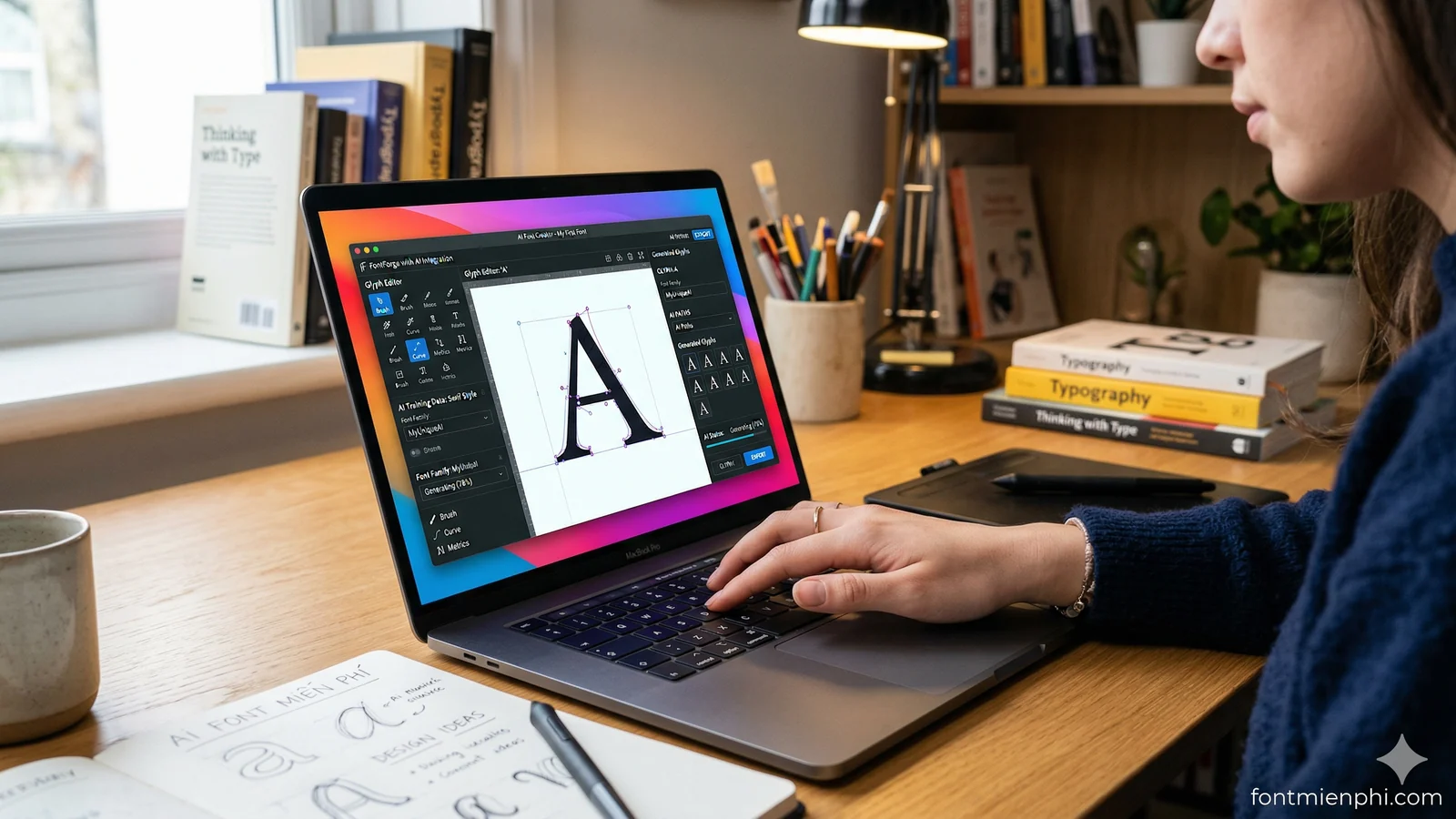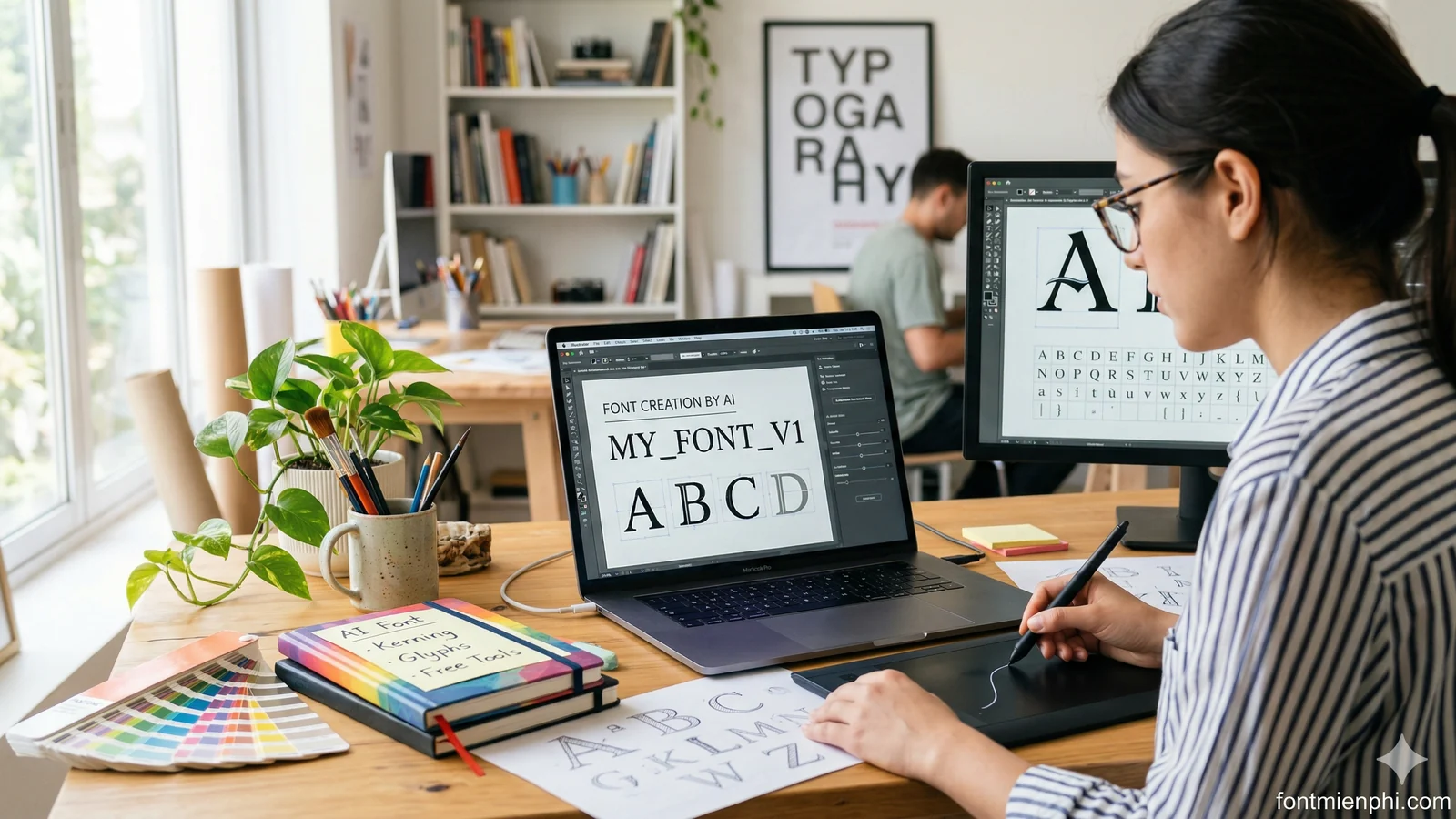
Bài viết này cung cấp hướng dẫn chi tiết về quy trình thiết kế bộ phông chữ cá nhân hóa bằng công nghệ trí tuệ nhân tạo mà không tốn chi phí. Bạn sẽ được tìm hiểu từ bước lên ý tưởng, sử dụng các công cụ AI tạo hình chữ cái cho đến việc số hóa chúng thành tệp định dạng chuẩn, giúp người mới bắt đầu dễ dàng làm chủ nghệ thuật chữ viết kỹ thuật số.
Cách Tạo Font Chữ Riêng Bằng AI Miễn Phí Dành Cho Người Mới
Thế giới thiết kế đồ họa đang trải qua một cuộc cách mạng mạnh mẽ nhờ sự can thiệp của trí tuệ nhân tạo. Trước đây, việc tạo ra một bộ phông chữ hoàn chỉnh đòi hỏi hàng tháng trời làm việc tỉ mỉ với các đường vector và kiến thức chuyên sâu về khoảng cách chữ. Tuy nhiên, hiện nay, ngay cả những người không có nền tảng về thiết kế cũng có thể tự tạo cho mình một bộ font chữ độc bản chỉ trong vài giờ đồng hồ nhờ sự hỗ trợ của các công cụ AI miễn phí.
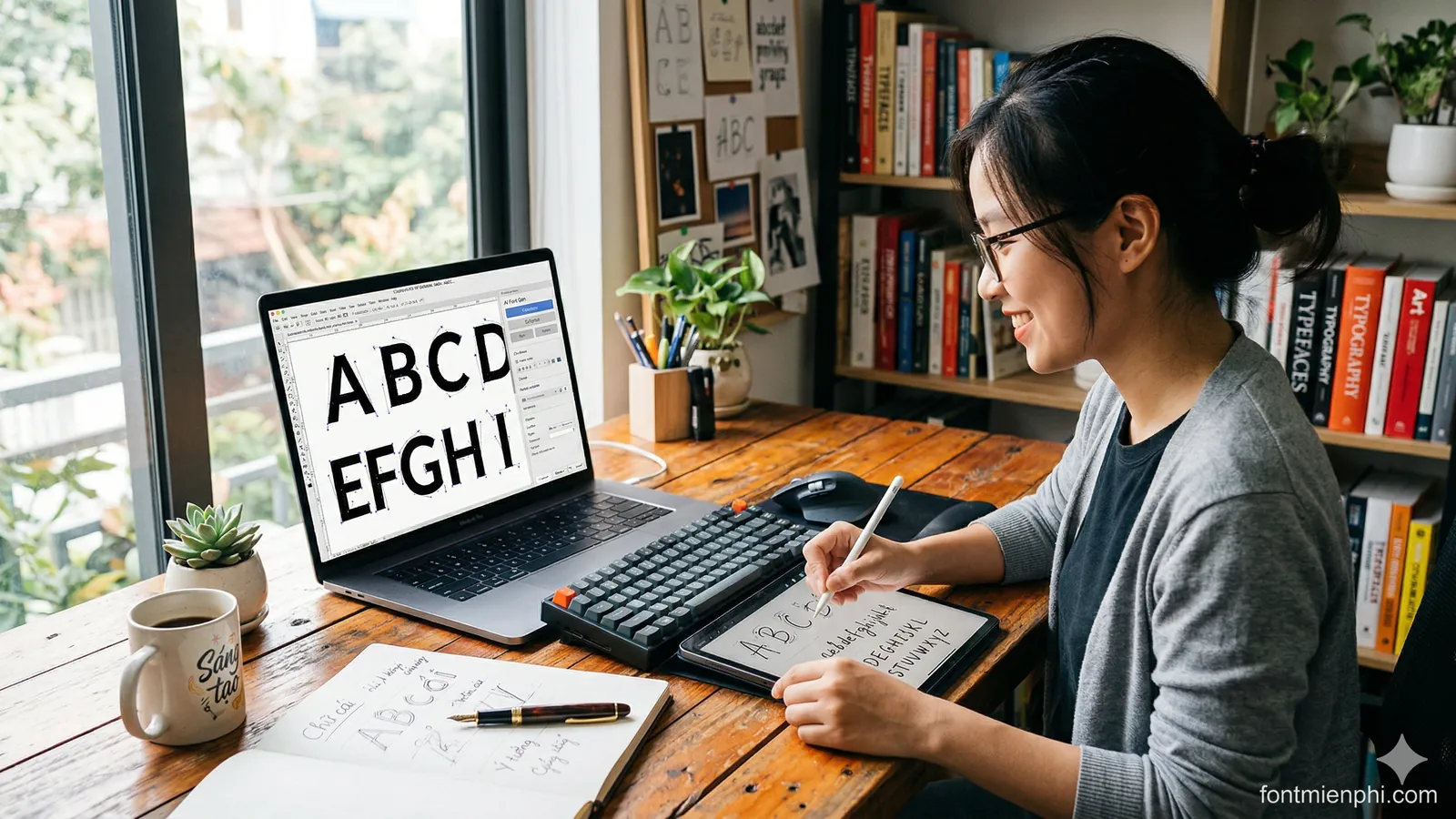
Tại sao bạn nên tự tạo font chữ bằng AI
Việc sở hữu một bộ phông chữ riêng mang lại nhiều giá trị thiết thực cho cá nhân và thương hiệu.
Tính độc bản: Font chữ của bạn sẽ không trùng lặp với bất kỳ ai, tạo nên dấu ấn nhận diện thương hiệu mạnh mẽ.
Tiết kiệm chi phí: Thay vì phải mua bản quyền các bộ font đắt đỏ, bạn có thể tự tạo ra sản phẩm tương đương.
Tự động hóa quy trình: AI giúp xử lý các công việc lặp đi lặp lại như cân chỉnh độ dày nét và tạo sự đồng nhất giữa các ký tự.
Khám phá sáng tạo: Bạn có thể thử nghiệm những phong cách nghệ thuật mới lạ mà các phương pháp truyền thống khó thực hiện nhanh chóng.
Các công cụ AI hỗ trợ tạo font chữ miễn phí phổ biến hiện nay
Để bắt đầu, bạn cần làm quen với một số công cụ hỗ trợ. Dù hiện tại chưa có một công cụ AI duy nhất nào thực hiện trọn gói từ khâu lên ý tưởng đến xuất file font chỉ bằng một cú click, nhưng sự kết hợp giữa chúng sẽ mang lại kết quả tối ưu.
Adobe Firefly và Midjourney
Đây là các công cụ AI tạo hình ảnh từ văn bản hàng đầu. Bạn có thể sử dụng chúng để tạo ra các thiết kế chữ cái đơn lẻ hoặc bảng chữ cái theo một phong cách nhất định. Ví dụ, bạn có thể nhập lệnh để AI tạo ra các chữ cái có phong cách bong bóng, kim loại hoặc nét vẽ tay nghệ thuật.
Calligraphr
Đây là công cụ quan trọng nhất để chuyển đổi hình ảnh chữ viết tay hoặc chữ do AI tạo thành tệp font có thể cài đặt trên máy tính. Phiên bản miễn phí của Calligraphr cho phép bạn tạo tối đa 75 ký tự trong một font, đủ cho một bộ chữ cái tiếng Việt cơ bản.
FontJoy
Nếu bạn không muốn tạo font từ đầu mà chỉ muốn tìm kiếm sự kết hợp hoàn hảo giữa các phông chữ hiện có, FontJoy sử dụng học máy để gợi ý các cặp font có độ tương phản và hài hòa cao, giúp bạn có thêm cảm hứng cho thiết kế của mình.
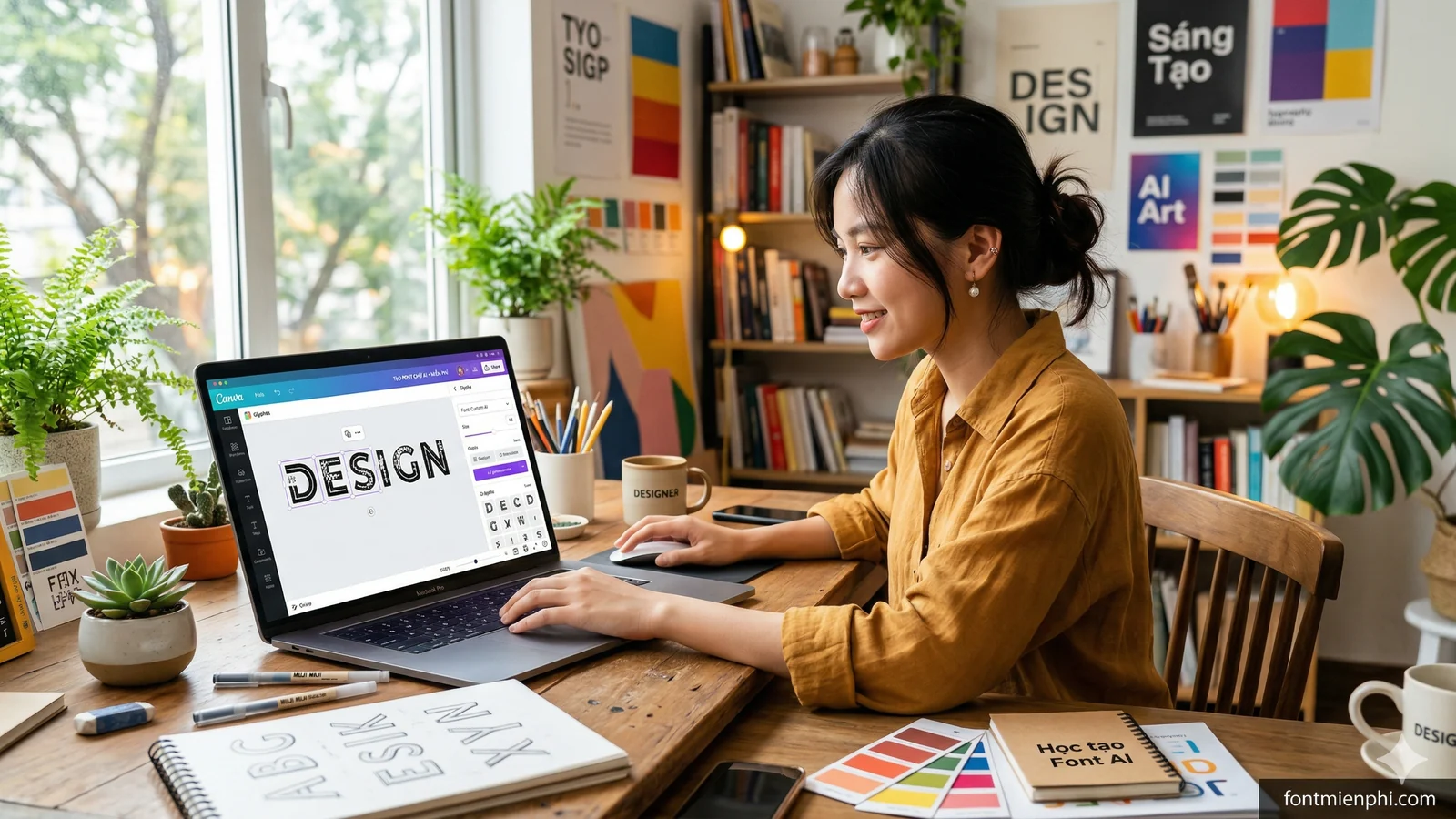
Quy trình chi tiết tạo font chữ bằng AI cho người mới bắt đầu
Dưới đây là các bước thực hiện cụ thể để bạn có thể biến ý tưởng thành một bộ phông chữ thực thụ.
Bước 1: Lên ý tưởng và xác định phong cách
Trước khi chạm vào các công cụ công nghệ, bạn cần xác định font chữ của mình sẽ phục vụ mục đích gì.
Font tiêu đề (Display font): Thường có nét dày, độc đáo, dùng cho các poster hoặc logo.
Font văn bản (Body text font): Cần sự rõ ràng, dễ nhìn, khoảng cách chữ hợp lý để đọc lâu không bị mỏi mắt.
Font viết tay (Handwriting font): Mang đậm dấu ấn cá nhân, phù hợp cho thiệp mời hoặc blog cá nhân.
Bước 2: Sử dụng AI để tạo hình các ký tự mẫu
Bạn có thể truy cập vào các công cụ tạo ảnh như Bing Image Creator hoặc Leonardo.ai. Sử dụng các câu lệnh (prompt) chi tiết để AI hiểu mong muốn của bạn.
Ví dụ câu lệnh: A complete alphabet set of minimal sans-serif letters, black on white background, vector style, consistent line weight.
Sau khi AI trả về kết quả, bạn hãy chọn ra các ký tự đẹp nhất và có sự đồng nhất về phong cách. Lưu ý rằng AI đôi khi gặp khó khăn trong việc tạo toàn bộ bảng chữ cái cùng lúc, vì vậy bạn có thể yêu cầu tạo từng nhóm chữ cái (A-H, I-P, Q-Z) để đảm bảo chất lượng.
Bước 3: Chuẩn hóa hình ảnh chữ cái
Các hình ảnh do AI tạo ra thường ở dạng bitmap (pixel). Để chuyển chúng thành font chữ chuyên nghiệp, bạn cần xử lý qua các bước:
Tách nền: Sử dụng các công cụ xóa nền trực tuyến để giữ lại phần chữ đen trên nền trắng tinh khiết.
Tăng độ sắc nét: Sử dụng các công cụ phóng đại ảnh AI (upscaler) để đảm bảo nét chữ không bị vỡ khi đưa vào phần mềm chuyển đổi.
Bước 4: Sử dụng mẫu (template) từ Calligraphr
Truy cập vào trang web Calligraphr và đăng ký một tài khoản miễn phí. Tại đây, bạn sẽ tải về một mẫu PDF hoặc PNG chứa các ô vuông cho từng chữ cái.
Tải mẫu về máy tính.
Sử dụng các phần mềm chỉnh sửa ảnh đơn giản như Canva hoặc Photoshop để chèn các chữ cái do AI tạo ở bước 2 vào đúng các ô tương ứng trên mẫu.
Đảm bảo các chữ cái được đặt cân đối, không chạm vào đường viền của ô.
Bước 5: Tải mẫu lên và tạo font
Sau khi đã điền đầy đủ các chữ cái vào mẫu, bạn tải tệp đó ngược lại lên Calligraphr. Hệ thống sẽ tự động quét và nhận diện các ký tự. Bạn có thể điều chỉnh thủ công khoảng cách giữa các chữ (kerning) và độ cao thấp của từng chữ cái nếu thấy cần thiết. Cuối cùng, nhấn vào nút Build Font để hệ thống xuất ra tệp định dạng .ttf hoặc .otf.
Sử dụng AI để tạo font chữ không chỉ là một quá trình kỹ thuật mà còn là một hành trình khám phá nghệ thuật đầy thú vị. Bằng cách kết hợp khả năng tính toán của máy móc với tư duy thẩm mỹ của con người, bạn có thể tạo ra những tác phẩm chữ viết mang đậm dấu ấn cá nhân mà không cần phải là một chuyên gia đồ họa lâu năm. Hãy bắt đầu với những ký tự đơn giản nhất và dần dần nâng cấp kỹ năng của mình qua từng bộ font.